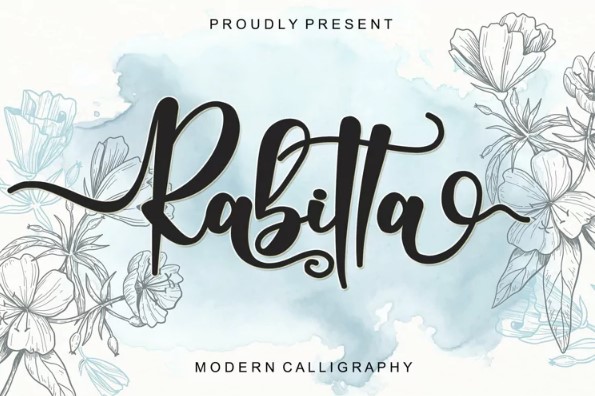
Fontbundles Rabitta Font
[Fontbundles] Rabitta Font
Шрифт Rabitta - это современный каллиграфический шрифт от Letterafa Studio.
Он имеет плавные буквы, которые придадут вашему дизайну уникальный и милый вид с множеством милых символов.
Шрифт Rabitta идеально подходит для логотипов, поздравительных открыток, дизайна упаковки, фирменного стиля, ремесленного дизайна, любых DIY-проектов, названия книг, свадебных приглашений, упаковки и многого другого.